相信大家都碰到过这样的情况:有时候总感觉使用普通的字库字体表现力不够,完全进行字体设计又费时费力。其实这时候,我们完全可以采取一些相对简单又容易出效果的方法,而笔画置换法就是其中一种。使用这种手法,我们可以通过现成的字库字体来完成创作。即便没有成熟的字体设计技能,仍然具备很强的可操作性。
今天,主要给大家介绍的笔画置换思路分为三种,分别是借用西文字体、日文假名以及汉字书法来进行置换。当然,从本质上来说,它们都是在进行不同字体的拼接。下面,我们先来讲用西文字体替换的部分。
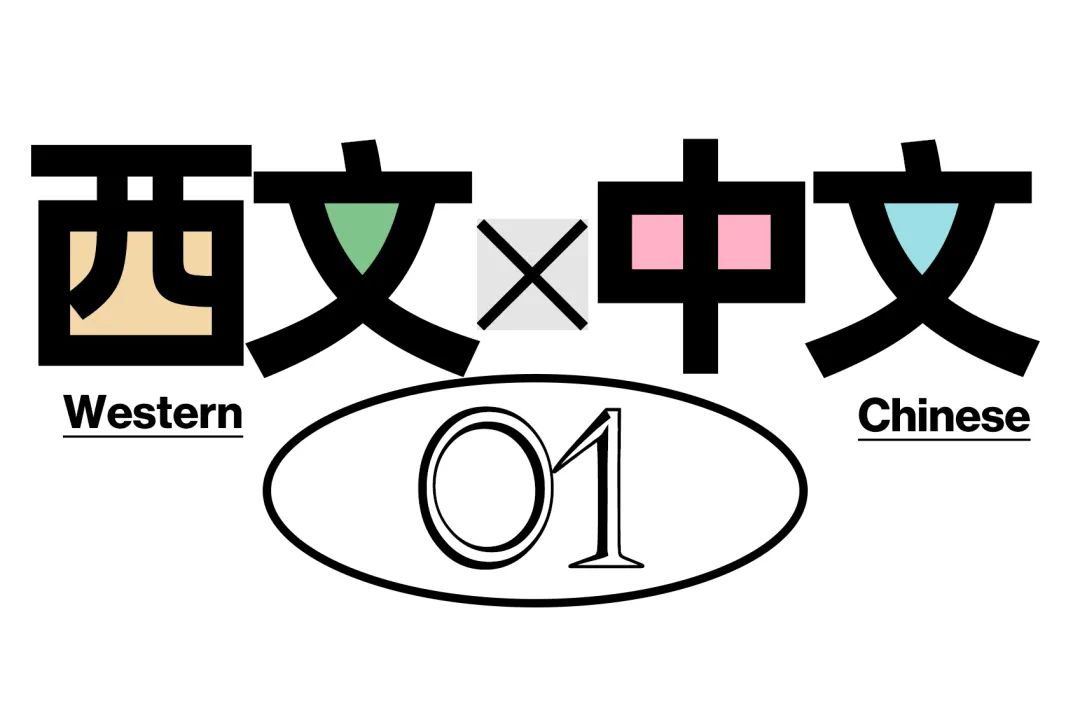
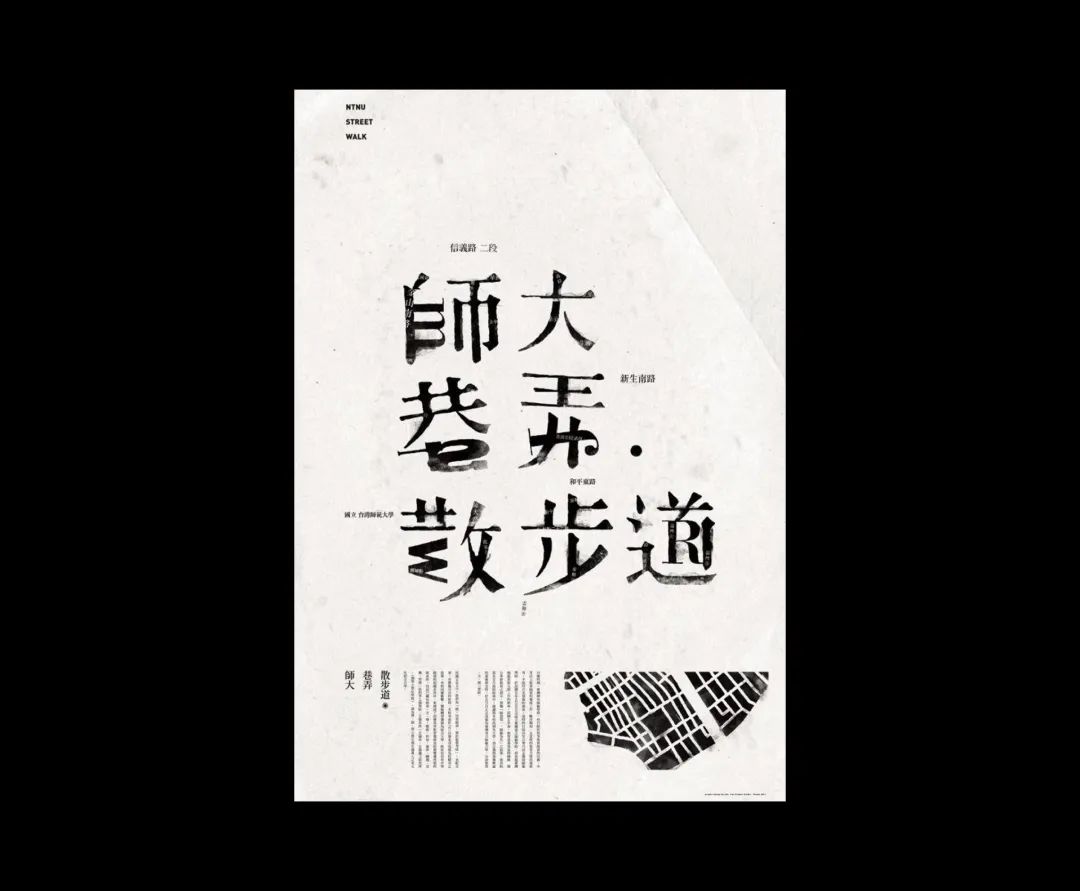
首先我们来简单看一下行业里大家是如何去做的。比如在这个作品中,就用到了多种西文字体来进行替换,来达到一个多种对比效果。其中,字母「m」「J」「R」使用了常规的衬线体,字母「S」使用了粗衬线体,这里的「S」是经过镜像翻的,另外还有字母「W」使用了无衬线体。而汉字的部分则统一是宋体。
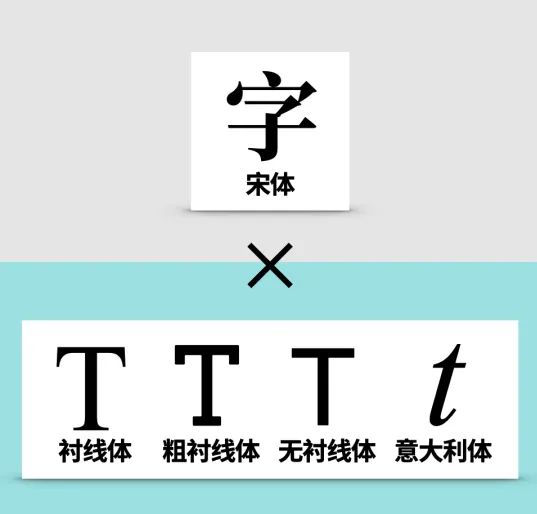
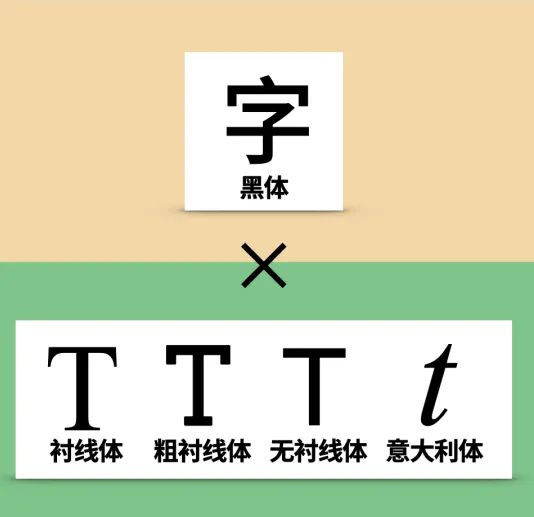
不难看出,如果大家使用宋体为基底来进行与西文字体的置换,西文字体的选择范围还是比较广泛的,可以是衬线体、意大利体、粗衬线体、或是无衬线体等。这其实就与我们做版式设计时进行字体搭配的思路是一样的。那么根据这样的推断,我们不难想象,对于以黑体为基底的汉字来说,同样也可以搭配这几种相应的西文字体类型。
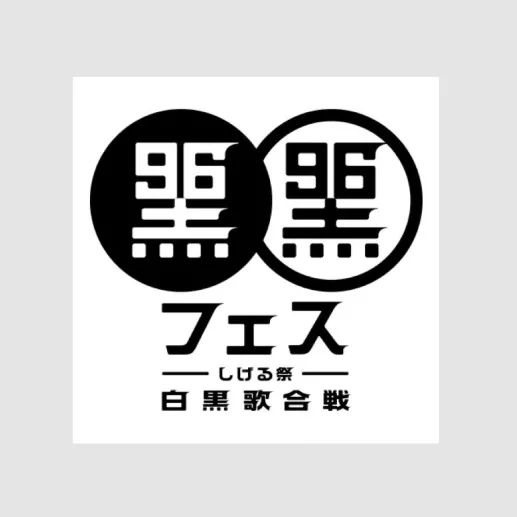
至于究竟选择哪一种,还得看我们具体想呈现出怎样的视觉印象。并且从制作难度的角度来考虑的话,字体间的对比越大,一定是越难把握的。
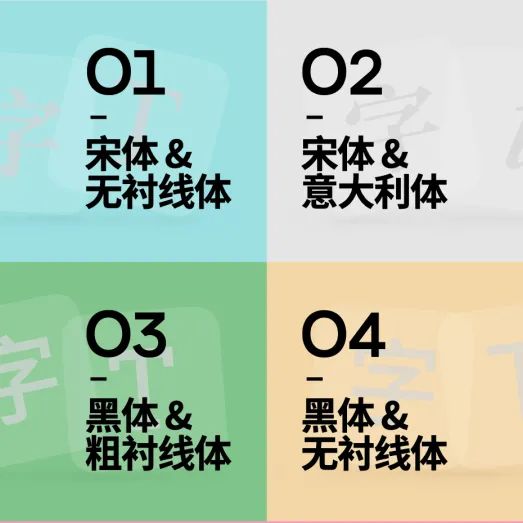
所以从最简单和容易出效果的角度出发,我们更推荐大家这四种搭配方式,分别是宋体与衬线体,宋体与意大利体,黑体与粗衬线体,以及黑体与无衬线体。
而再回过头来看这些作品,这一回我们不看字体搭配,转而观察西文字体在置换时出现的频次。
可以看到,基本上同一个汉字,最多只会置换一次完整的西文单字,这样既能保持良好的识别度,也不会有太高的制作难度。
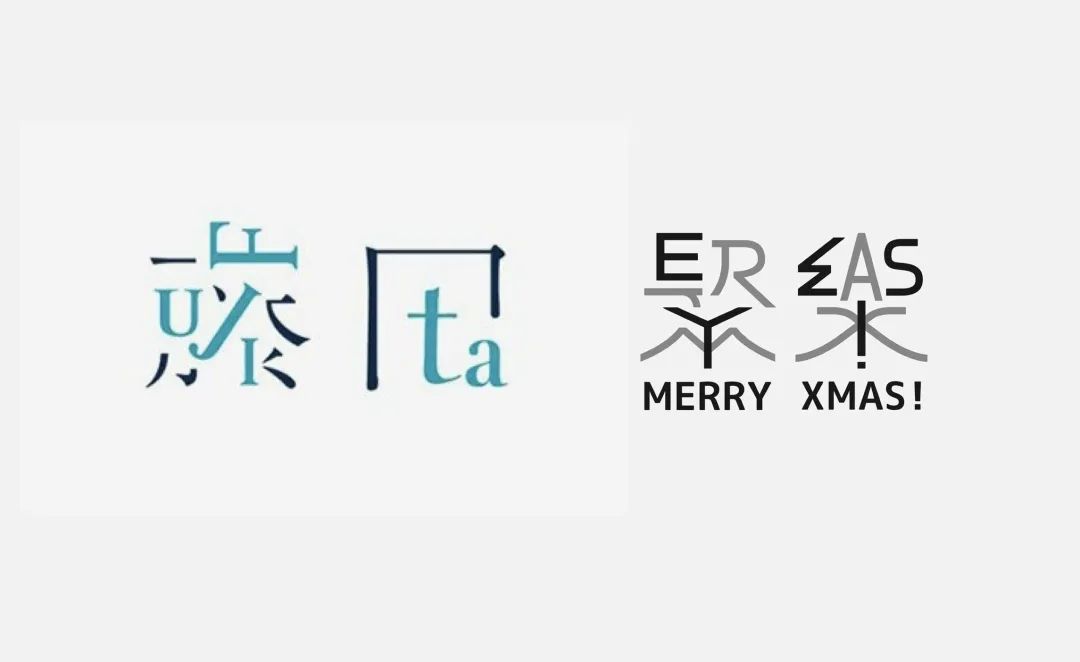
当然,如果能力足够,也是可以同时使用多个字符来进行置换,但是这无疑已经超过今天我们要探讨的范围了。
下面我们也来应用一下这个方法制作一个简单的案例。大家也可以找来一个合适的文案进行自我练习,比如这里我选择使用「梦幻岛」这三个字。
首先要过的第一关当然是汉字字体的选择了,毕竟西文字体也是根据汉字的字体类型来搭配选择的。对于梦幻岛这三个字,显然宋体字会更加满足我们对「梦幻」二字的想象。
当然,如果再精益求精一些,我们还需要进而选择一款更加贴切的宋体,比如这里第一款,边边角角过于简洁,直来直去,并不够梦幻;而第二款笔画虽然足够圆润,但是结构太过紧缩,古典意味明显,也不在考虑范围内;第三款宋体不仅结构足够开阔,横竖笔画对比明显、转角还有圆角的处理,整体更有一种若即若离的梦幻感。所以我们这里选择使用第三款宋体。
选好字体以后,就可以逐一对单字「做手术」了,我们需要找到汉字中可以被替换成英文的部分,并完成替换。
比如在这里「梦」字上方的两个木字形部件中,我们以找到近似于大写英文字母「T」的部分,这时候就可以直接把「T」拿过来尝试替换。但是把T放大到合适的粗细时,整体就太大了,这时候我们只需要对字母进行一个笔画长短上的调整即可。
第二个「幻」字,最明显又容易改动的地方当属右边横折钩了。这里竖钩的造型一下就能让我们联想到英文字母中的「J」,因为刚才我们已经使用了大写字母来作为替换,所以出于统一性的考虑,我们依旧使用大写的「J」来替换。可以看到,替换之后整体依然显得十分和谐,甚至如果让一个不太懂宋体构成的朋友来看,估计都挺难发现其中的奥妙。
接着,我们来看最后一个「岛」字,繁体的「岛」字整个上半部分由大量的横竖画组成,并且一体感较强,想要对这部分动手还需要多加斟酌,所以下半部分的山字才是我们的第一目标。
在大写字母中,恰好有字母「E」能与汉字的「山」在字形上有所呼应,只需要将「E」逆时针旋转九十度就可以做到。
直接将「E」替换掉原本的部件,当然这里面我们还需要像之前的「梦」字那里一样,去简单调整一下「E」字的比例关系,让它能够被安放在这样一个小的空间里。
这就是我们在最短时间内修改好的三个字,这一次的尝试整体更加保守一些,虽然对汉字的结构做到了尽可能的保留来满足辨识度,但是整体太过呆板,缺乏了一些中西合璧所应具备的亮眼之处。所以我们可以选择重头再来一遍,看看有没有更好的处理思路。
这一次我们可以尝试对下面的夕字进行替换,从整体来看,能与夕字在外形扯上关系的只有意大利体中的大写A了。
然而当我们尝试替换以后,不难发现,虽然识别度勉强过得去,但是更强烈的感觉还是替换得太过僵硬,上下的统一感有所欠缺。除非我们是自己有意想营造这种感觉,不然就显得很应付。
并且本身意大利体的标准模式该是小写才对,所以我们这里直接把选择范围再一次缩小,这一次的替换我们只是用小写的意大利体。而在这样的范围下,能和「夕」字扯上关系的字母就完全没有了。
所以我们减少需要被替换的范围,去掉中间的一点,只保留一个外框,我们可以在脑海中复现一下外框的笔顺,加上外框的造型,很容易让我们联想到小写意大利体的「n」。
替换过后,可以发现不仅不会影响字形的正常识别,并且意大利体自身的手写感也充满了一种微妙的感觉,非常容易衬托出字义的氛围。当然,我们还需要继续对「n」进行一个粗细上的调整,让它更加融于整个字形之中。
接着来看「幻」字,置换的部分这次我们依然选择竖钩的部分,而所替换的字母还是选择「j」,毕竟没有比这俩兄弟更适合互相转化的组合了。不过因为意大利体本身就具备倾斜的属性,所以在拼接的时候没有办法放在一个最满意的位置,比如右上角的地方难免有些超出了原本的字面大小。本着只做微调的出发点,这里我们就不对「j」进行倾斜角度上的调整了,而是适当延长原本汉字上面的一横,让他们相交而成为一个整体。拼好后的字虽然易于辨识,但是难免有些小问题,这个我们之后再统一解决。
最后一个岛字,依然替换下面的山字部件,不过这一次我们不可能再使用大写的E来完成拼接了。往后依次查找,可以看到小写的m似乎是一个可行的替换方案。不过,m的开口朝向和山字完全相反,这里我们选择把字母旋转180度来让m的开口朝向变为上方。适当调整文字,让它看起来和山字部件差不多大小即可。
另外还可以使用字母「w」来替换,过程和「m」相似,不再赘述。直接对比两种方案,显然是「w」的方案更胜一筹,左边「m」因为经过旋转,整体的书写流畅度看起来差了许多,并且原本旋转前的起笔处与「岛」的勾画相冲突,只能避让开,而右边「w」方案就不会有这样的问题出现。所以我们选择后者。
现在我们把三个字放在一起观察,不难看出原本单字看起来还可以的造型,当它们组合在一起后,就显得有些歪歪扭扭了,并且负空间也有一些小问题不太好解决。如果大家不具备字体设计的能力,去过分调整笔画就不是一个可行的路数,应该怎么办呢?
既然西文部分选用了意大利体,那么汉字部分我们也可以选择倾斜一定的角度来形成一致的动势,这样不但是单字本身,字与字之间也显得更加统一和谐。
这样我们的西文字体置换汉字笔画的小案例就大致完成了。
最后可以配上一定的文字与装饰元素,进一步烘托氛围。总的来说这样的方法还是考察大家的观察能力与联想能力,执行起来并不具备很高的难度,只需要会基本的软件操作就能完成,并且能在短时间内完成且具备不错的效果,性价比极高。
第二部分我们尝试将日文假名与汉字相结合。接下来,我们将把从构思到执行、从遇到问题到修改问题的整个过程完整呈现给大家。
我们先来对比一下,日文和中文都有哪些相同点和不同之处。首先,我们会发现,在日文里面是存在汉字的,虽然它们的写法和我们的简体字不太一样,但我们也能很直观的认出它们。
其次,日文中除了汉字之外还存在假名。也就是我们画面里现在标注着蓝色的部分。它们才是日文中最有代表性的符号,也是我们区别日文和中文的最直观的手段。
在简单对比日文和中文之间的差异后,我们就需要思考,应该如何将汉字与假名巧妙地结合在一起。
那么根据结合汉字和假名的这样的需求,我们不妨选择「鉴真东渡」这个主题来进行演示。要知道在这个时期,正是日本全面学习中华文化的时候,这样的内容与技法本身也具备很强的联系性。
像这样具备历史感和文化感的主题,当然是首选宋体去进行创作了。不过,我们看画面中的这三种宋体类型,他们仍然会传达出不一样的视觉感受。
为了更加贴合信息本身带有的情感属性,我们可以选择最下方这款中宫收紧、笔画带有明显书法特征的传统型宋体。
那么汉字部分到这里,就基本选好了,接下来我们看看日文假名的部分。
在选择日文假名的时候,我们会遇到一个小问题,其实很多中文字库是内建有假名的。那么有些同学可能会觉得,使用同一字库中的字符,统一性该是最好的才对吧?
答案是否定的,或者说不能一概而论。许多中文字库内建的假名其实品质并不算上乘,所以我们通常不建议大家直接使用中文字库中内建的假名,选择合适的日文字库也是必要的。
而在假名的列表中我们可以发现,其实有几个字符本身就与汉字中的一些基础笔画极为相似。没准我们可以从这里入手,开始进行组合。
首先,我们把横划的部分全都替换成假名的样式。紧接着是所有有顿点的地方,接下来是所有带有「撇」的部分。到这里,我们可以稍作停顿来思考一下,似乎有哪里不对。现在的版本是不是没有日文的特征了?好像完全变成了楷体的样式。那么,我们又要怎样去体现假名的视觉印象呢?
我们知道,日文中的假名部分其实是从汉字的草书演变而来的,那么基于这个规则,我们可以从草书的写法这个点切入。
我们不妨先多多查看这几个汉字的行草写法,在脑海里有形成一个基础的印象,然后我们就可以根据写法去寻找对应的假名结构,逐步完成拼接。
接着我们就需要针对逐个问题进行修改。这里我们用这个绿色的线框去表示修改前的样式,黑色的字代表修改后。经过结构上的调整,我们对比绿线和黑色的部分,可以看到调整后的文字结构明显要更稳定一些。
大家注意看调整后的样子,发现我都修改了哪些地方?首先假名的部分被继续调整到了一个相对舒适的部位,另外呢,为了让整体看起来更有标题的感受,我们把横笔的部分减少了一半,这样文字的比例感就显得更宏观了。
那么最后,
我们来看一下完整的
字型展示吧!
汉字中最常见的结构就是左右结构和上下结构。那我们替换笔画的第一个方法,就是直接去替换字的偏旁部首。
比如说这个字,我们可以直接替换整个马字旁,但是替换的时候要注意,我们也要去参考原笔画的结构比例,比如这里的马字旁就显得有些大了,整个字的结构比例失衡之后就会被人看成两个字。
所以在做的时候可以把原字体的笔画透明度调低,方便我们参考对照。替换一个小一些的马字旁,然后我们可以去参考书法字的结构和笔画之间的关系进行微调。
在笔画少的时候,可以选择替换比较稳定的笔画。如果想要更加收敛的感觉,我们也可以去替换一些不那么重要的笔画。
刚才说的都是单独的字,那多个字该怎么替换呢?我们可以按照之前的规律来试一下。这里可以选择替换这几个笔画里比较容易出效果的部件或笔画。
换之后我们可以感觉到,整体灰度不匀称,笔画看起来显得也是比较乱,这是为什么呢?因为黑体搭配书法笔画对统一性的要求更高,在字多的情况下对比就更加难以处理。
那我们可以换一个思路,用一款圆润的宋体去搭配书法笔画。替换的时候需要多加注意笔画灰度匀称。宋体本身是具备笔画粗细对比的字体,所以我们在替换宋体笔画时只要注意好书法笔画的轻重与原笔画基本一致,就不容易出错。